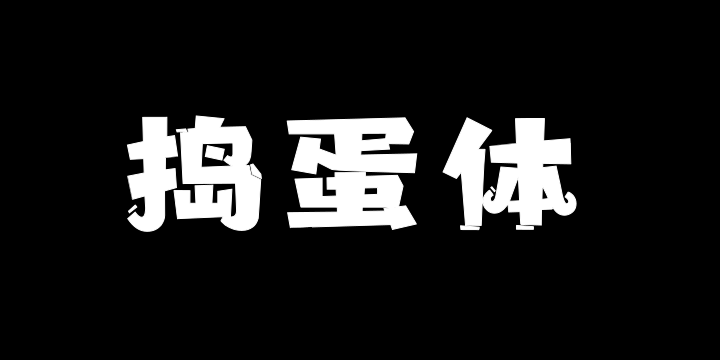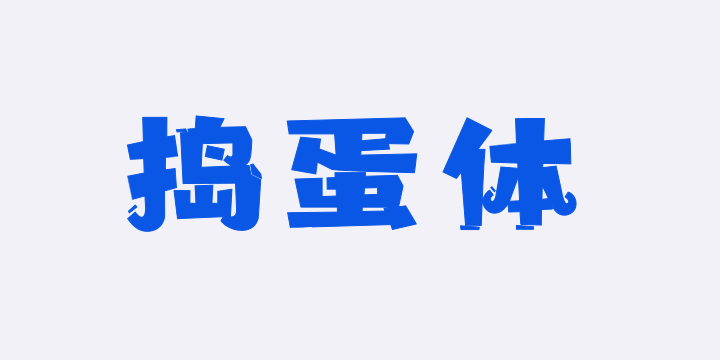
上首捣蛋体 By 上首造字 商用字体
字体全名: 上首捣蛋体
铸字厂: 上首造字
设计师: 胡博剑
字体简介: 上首捣蛋体,简体中文约6763字,字体俏皮可爱,笔画上进行了梯形外观调整,每个字的笔画都跳出了常规的板正状态。简洁随性不矢细节,使单调简约的字体丰富起来,此款字体多适用于包装、海报、文艺、创意广告等领域。